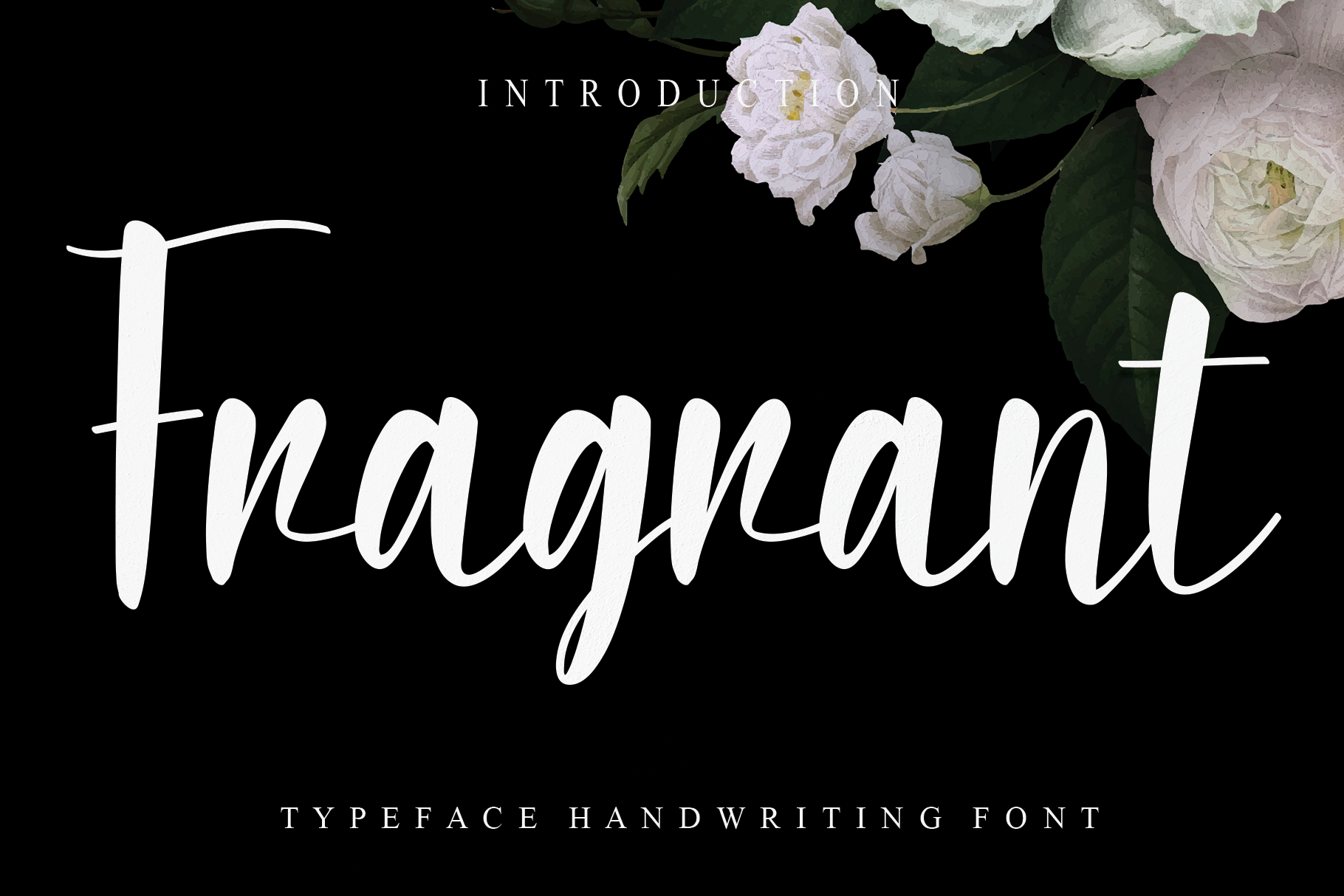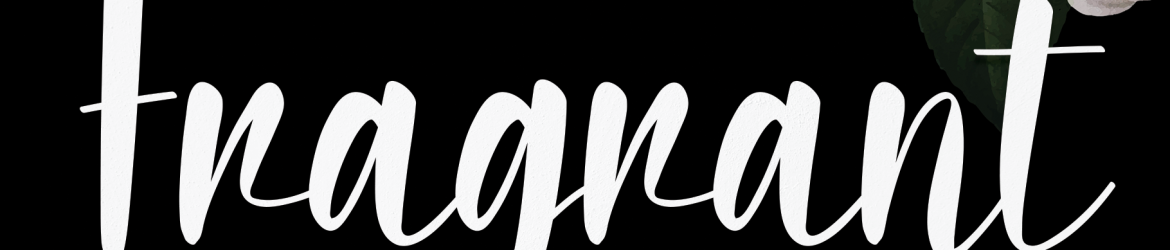
Fragrant Font – Download Grátis
A Fragrant Font é uma fonte escrita a mão criada com um toque sofisticado e autêntico. Ideal para quem busca um toque especial em projetos que precisam de um ar pessoal, essa fonte pode ser encontrada desde o design de embalagens até as criações gráficas digitais. Suas linhas elegantes e nuances sutis criam uma sensação de conforto e sofisticação, tornando-a perfeita para anúncios, convites de casamento e mesmo como um marcador de página em livros autênticos. Com seus traços delicados e estilo único, a Fragrant Font oferece o desejado toque criativo ideal para design de arte digital, design gráfico e criação de logotipos. Perfeita para destacar sua marca ou mensagem na web, seja em postagens nas redes sociais ou como um logo no seu site. Além disso, a Fragrant Font também é adequada para qualquer projeto que possa beneficiar da escrita a mão, desde etiquetas e embalagens até a criação de capas de livros ou gráficos de publicidade. Escolha a Fragrant Font para adicionar um toque autêntico às suas próximas criações.